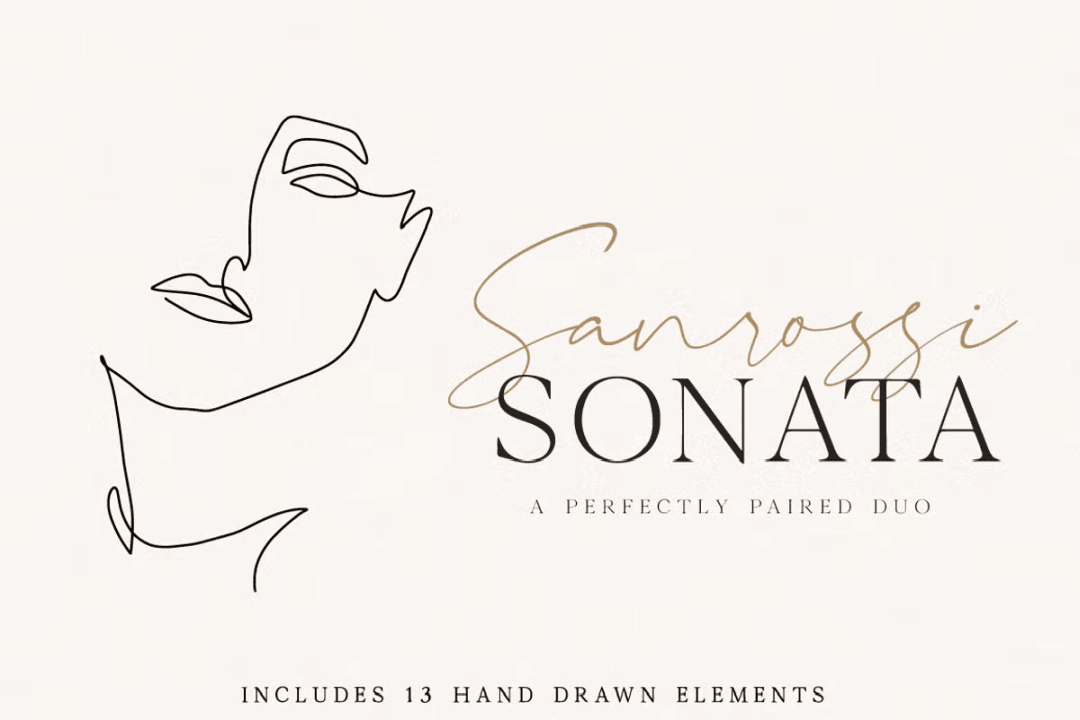
Sanrossi Sonata
エレガントなモダンローマンとスクリプトのデュオ。よくあるタイプといえばそうなのだが(笑)バレンタインに似合うので紹介する。ローマンの方は大文字はクセのない普通のグリフをしているが、小文字が画像にはないがやや角ばったおもしろい形をしている。アセンダーやディセンダーも極端に短く、この手としてはちょっと変わってる。スクリプトはゆったりしたストロークながらややスピーディ。画像の左に一筆書きのドローイングがあるが、このテイストのイラストが13種付属していて、ちょっとしたポスターなんかすぐ作れるようになっている。